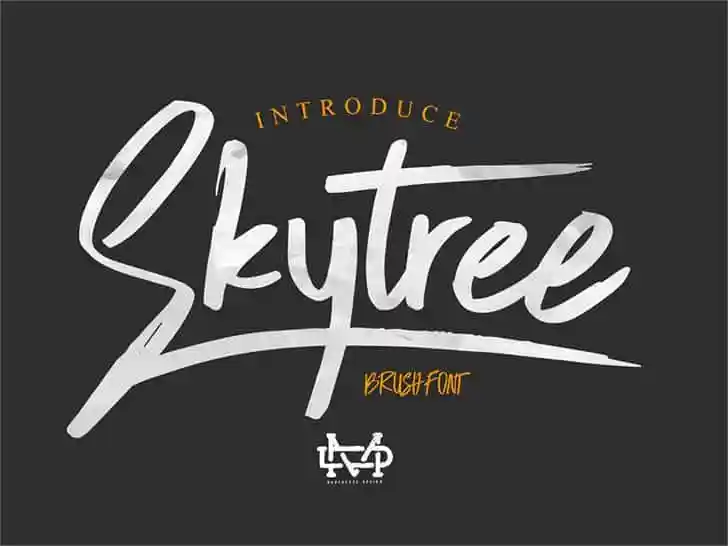
Skytree Typeface é uma nova adição à vasta gama de letras script disponíveis no mercado, criada pelo designer madeDeduk. Esta fonte moderna e sofisticada traz um toque de elegância ao seu design, perfeitamente adaptável para um amplo leque de aplicabilidades, desde designs digitais até eventos memoráveis. Seja você um designer gráfico ou simplesmente uma pessoa que busca adicionar um pouco mais de charme a seus trabalhos pessoais, Skytree é uma escolha ótima para quem procura uma fonte script moderna e inovadora. Não perca esta oportunidade para dar vida à sua ideia com uma letra poderosa e versátil.